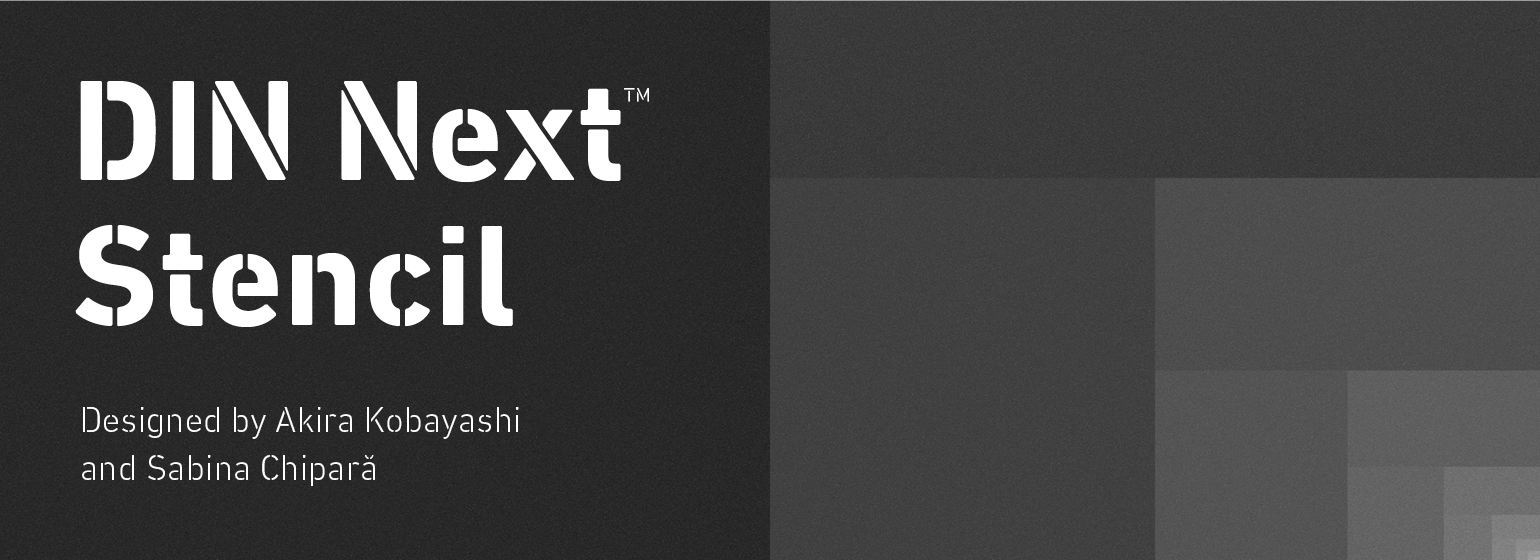
DIN® Next Stencil
DIN® Next Stencil,这款字体结构工整、笔画清晰,兼顾美观与易读性,适用于标题、正文、海报、包装、LOGO 等多种场景。字形优雅稳定,风格百搭耐看,适配日常排版与创意设计,让文字呈现更舒适、更具质感。DIN® Next Stencil一笔一画,皆是细节,以均衡的比例、流畅的线条打造舒适视觉体验,字形端正大气,风格简约现代。无论是商业设计、品牌宣传还是日常排版,都能轻松驾驭,让文字更有格调与力量。DIN® Next Stencil字体下载。
字体品牌: Monotype 设计师:Chipara,Sabina; Kobayashi,Akira 字体分类:衬线体 字体属性:外文 字符集:Unicode 发布时间: 2018